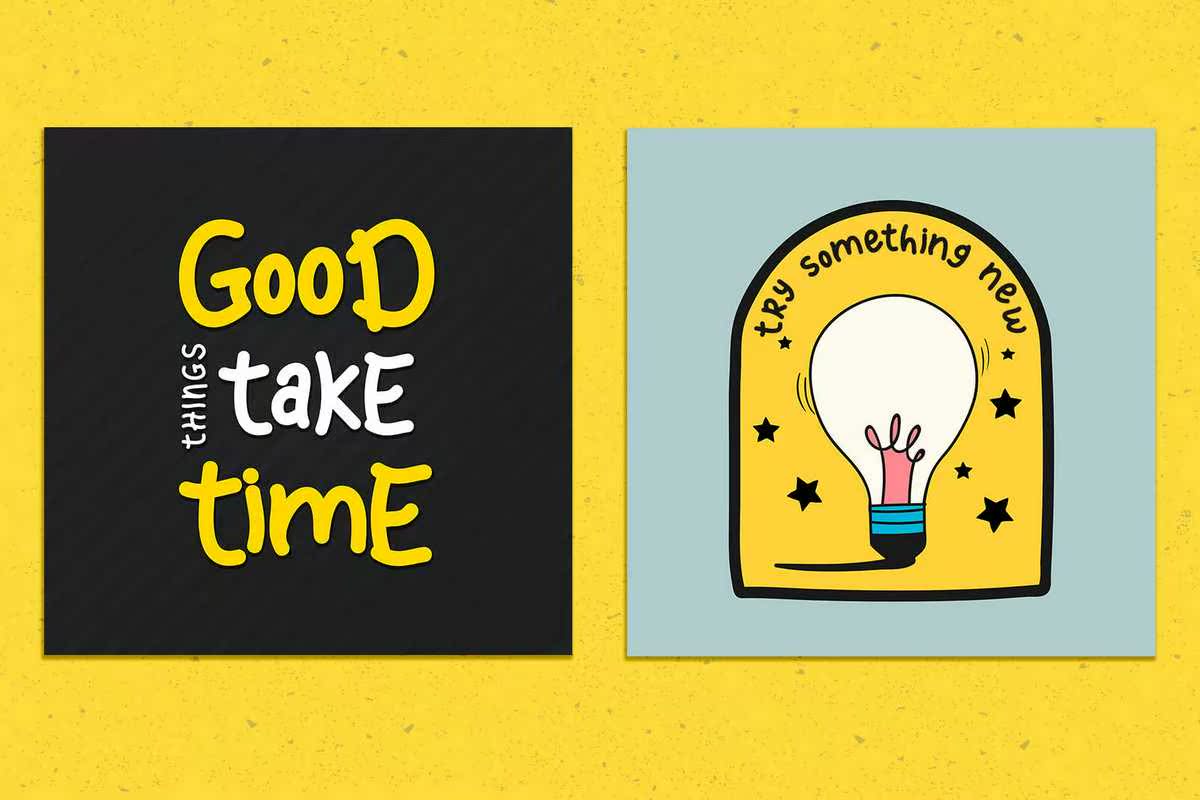
Cheerful Yellow是一种有趣而可爱的显示字体。它具有好玩的风格和良好的可读性。它适用于卡片、品牌、文具、博客设计、定制艺术、报价、定制邮票、定制浮雕、书籍、服装、包装、标题或更多!它将为任何设计项目增添独特的魅力!这是一个编码,意味着你可以访问这个密码!它还拥有丰富的连字。欢快的黄色是一种既有趣又可爱的显示字体。它风格活泼,可读性强。它适用于卡片、品牌、文具、博客设计、定制艺术、报价、定制邮票、定制浮雕、书籍、服装、包装、标题或更多!它将为任何设计项目增添独特的魅力!这是一个编码,意味着你可以访问这个密码!自然资源丰富,包括韧带。